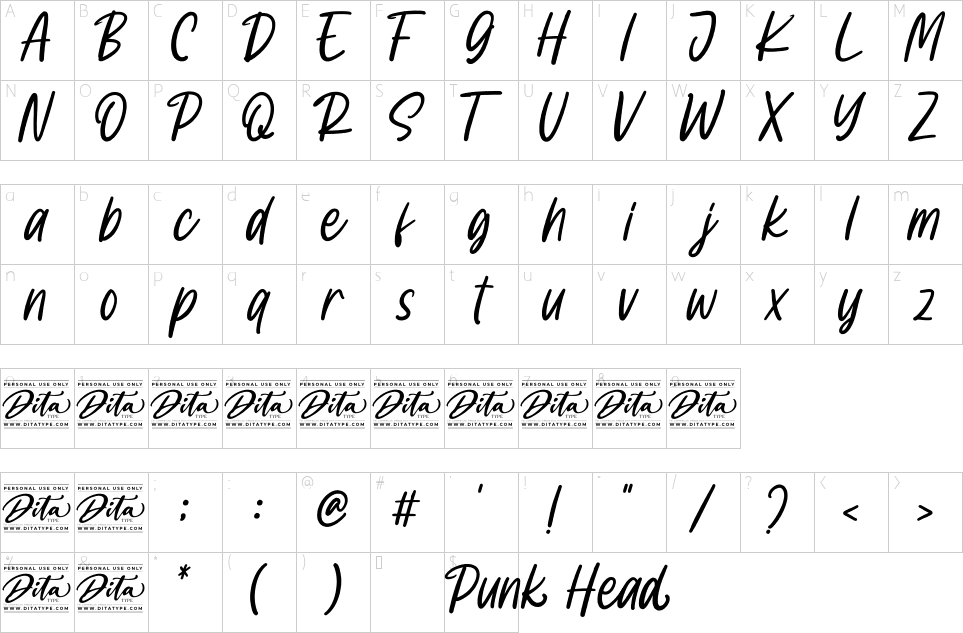
A fonte Punk Head é uma opção divertida e criativa para adicionar um toque único ao seu design gráfico. Desenhada pela Dita type, ela é ideal para quem procura uma fonte com estilo punk para seus projetos. Com sua design fluido e distintivo, a Punk Head pode dar um toque interessante e diferenciado a qualquer texto ou logotipo. Esta fonte já foi baixada mais de três mil vezes, indicando que muitos profissionais de design acreditam em sua eficácia. Seja para aplicações web ou em impressão, essa fonte pode ser um ótimo complemento para seu projeto. Não hesite em baixá-la e experimentar a diversão que ela traz para o seu trabalho de design.